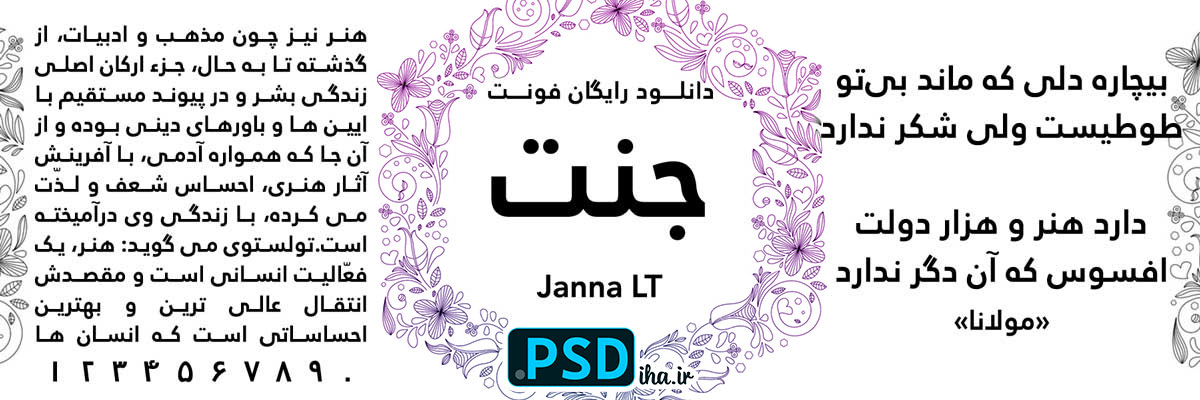
فونت عربی جنت
اگه دنبال فونتی هستید که همزمان رسمی باشه، اما اون همه خشکی و یکنواختی فونت‌های اداری رو نداشته باشه – فونت جنت انتخاب اول منه. طراحی نرم و خوش‌فرمش، مخصوصاً برای متن‌های بلند در کاتالوگ‌های آرایشی و بهداشتی، دعوت‌نامه‌های عروسی، یا حتی توضیحات محصولات لبنی و دمنوش، حس آرامش و اعتماد رو منتقل می‌کنه. مهم‌تر اینکه این فونت کاملاً از حروف فارسی «گ چ پ ژ» پشتیبانی می‌کنه، پس نگران به هم ریختگی نباشید.
از نظر چاپی، جنت روی کاغذهای مات و گلاسه هر دو عالی دیده می‌شه. من خودم توی طراحی کارت‌های ویزیت شیک و زنانه بارها ازش استفاده کردم – مخصوصاً وقتی فونت توی لوگو یا سمت شغلی مشاور و پزشک میاد، یه جذابیت خاصی به کار میده. همچنین می‌تونید در کنار این فونت، بقیه آرشیو فونت‌های سایت رو هم ببینید.